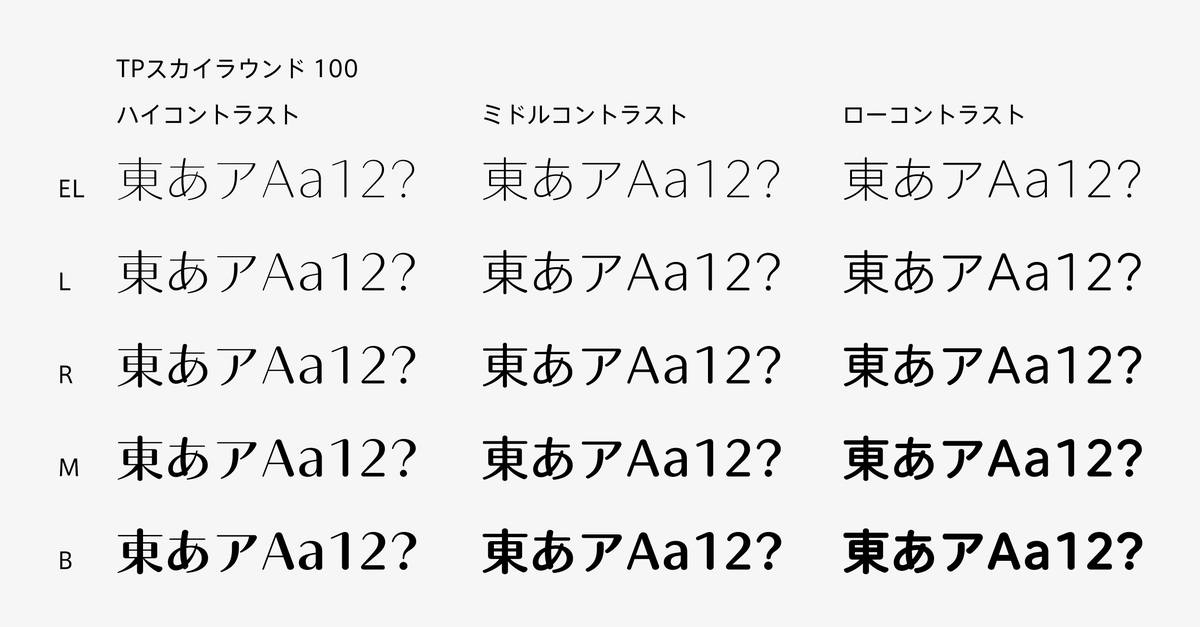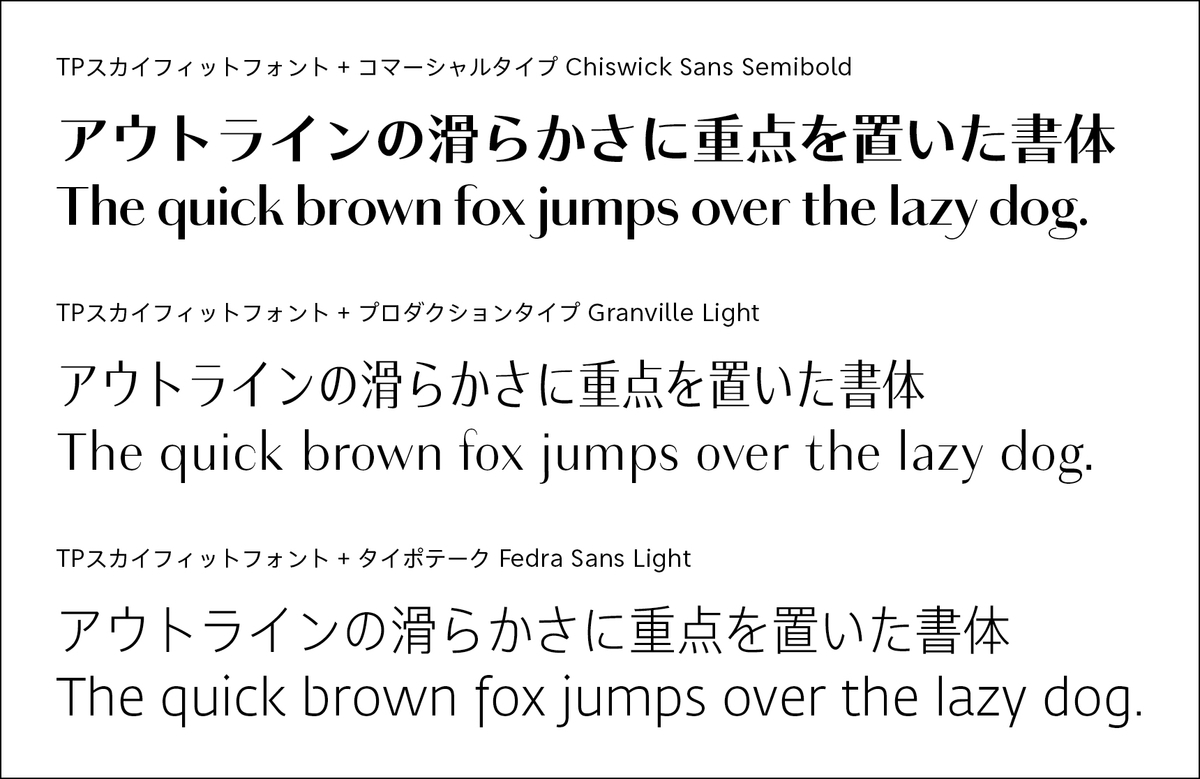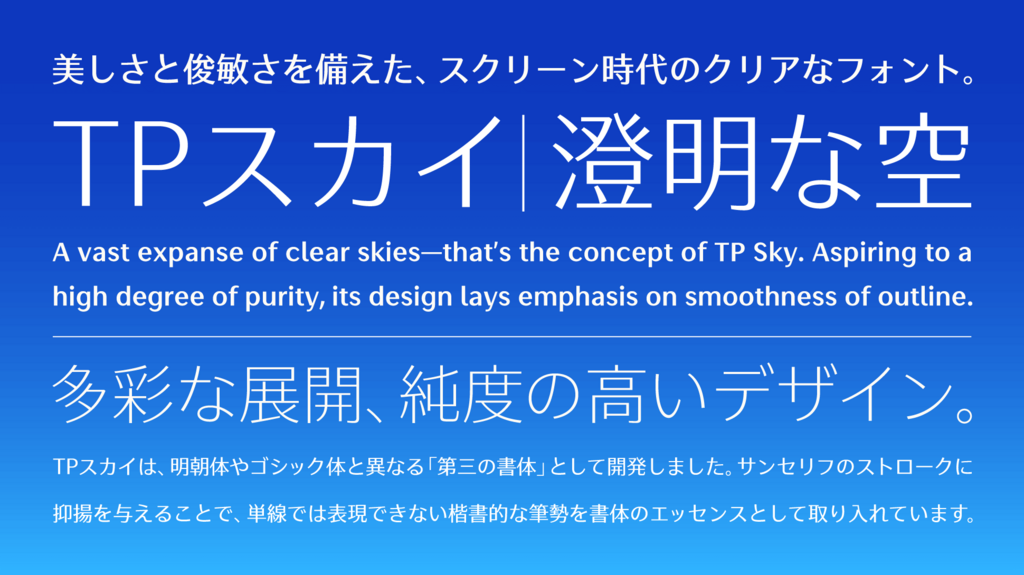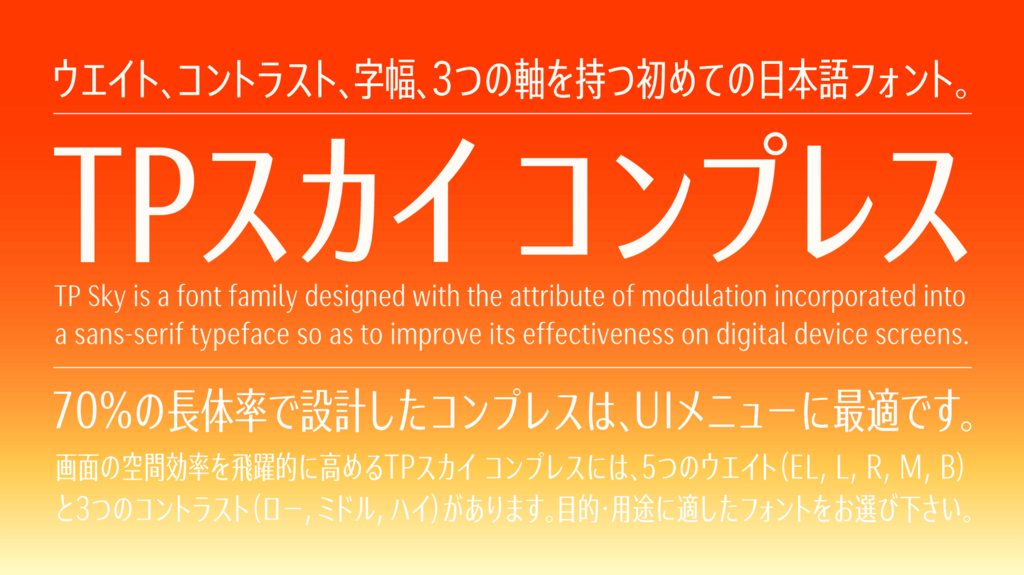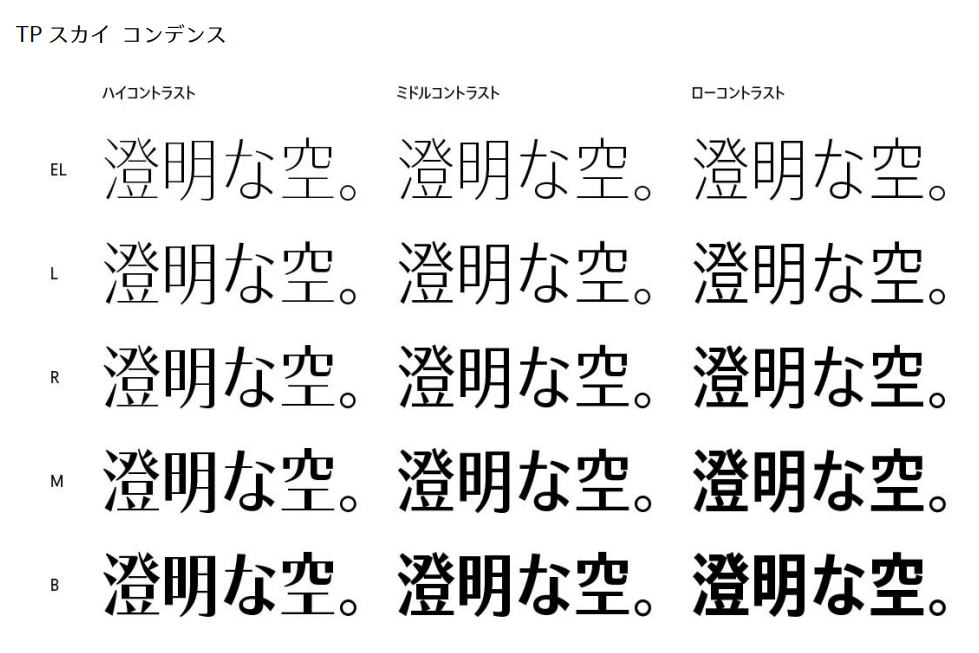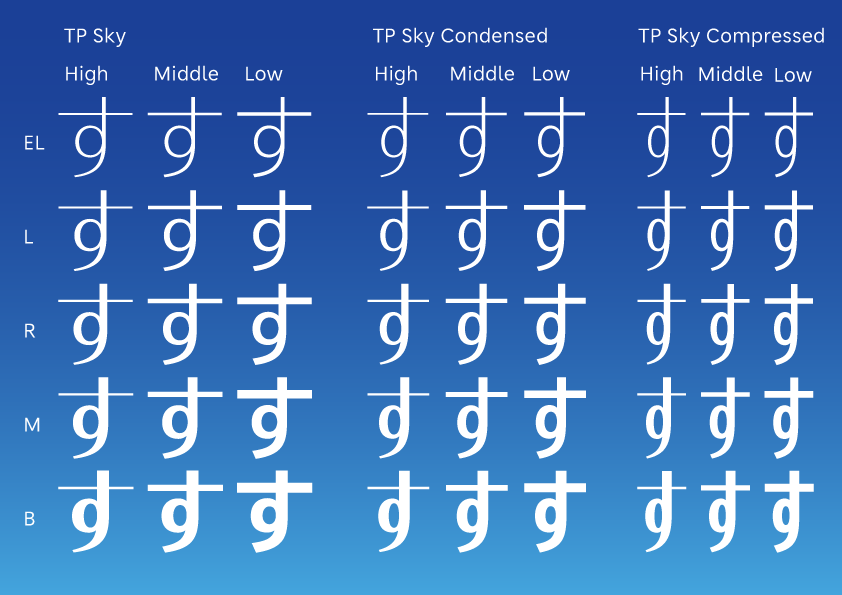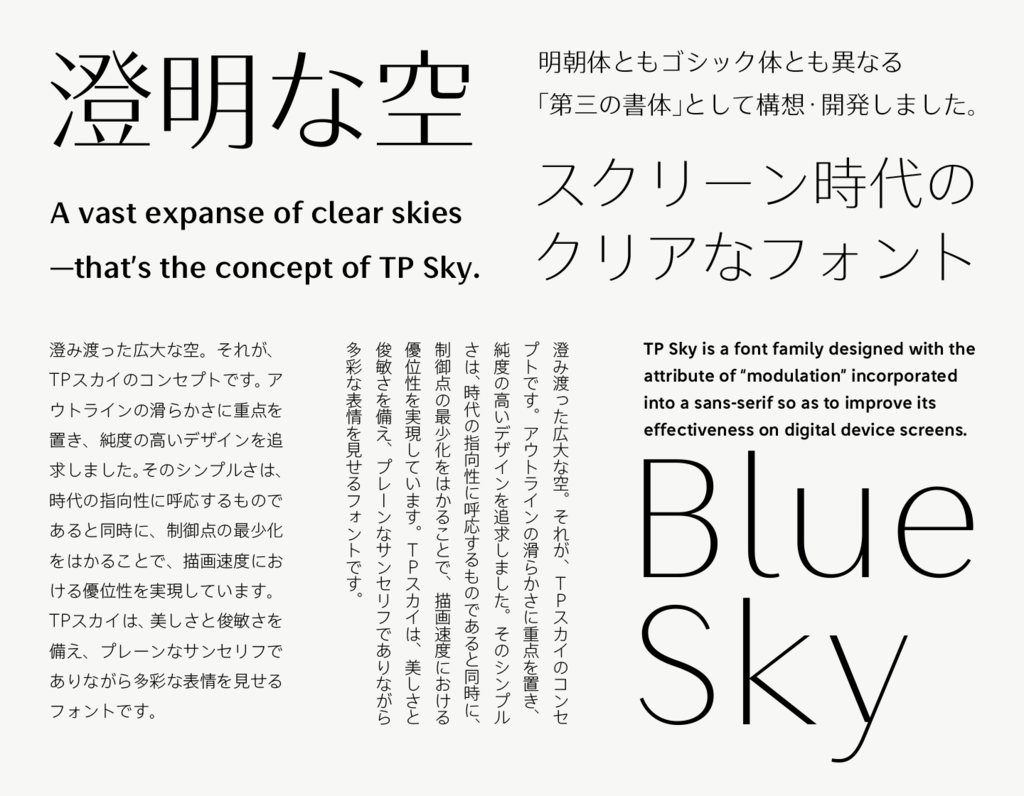
タイププロジェクトによる抑揚サンセリフ体TPスカイシリーズにラウンドフォント「TPスカイ ラウンド 50」「TPスカイ ラウンド 100」が発表
タイププロジェクトは、抑揚サンセリフ体であるTPスカイファミリーの新フォントとして、「TPスカイ ラウンド 50」および「TPスカイ ラウンド 100」を2019年5月16日に発表した。「TPスカイ ラウンドシリーズ」は、タイププロジェクトが提供するフォントを年間定額で利用できるサービス「TPコネクト」での提供となる。
「TPスカイ」は、スクリーン表示に適した本格的なフォントで、ウエイト・コントラスト・字幅の3つの軸を持つ初めての日本語フォントで、そのシリーズに、角アールの度合いを選べるラウンドが加わった。
「TPスカイ ラウンド50」と「TPスカイ ラウンド100」は、それぞれ3つのコントラスト(ハイ/ミドル/ロー) と5つのウエイト(EL/L/R/M/B) で構成され、合わせて30フォントのラウンドファミリーとなる。
タイププロジェクトの代表取締役である鈴木功氏は、「視認性が高いTPスカイの書体設計をベースに、ストロークの先端を丸めることで親しみやすさと使いやすさが格段に向上したと自負しています。横組み用途で開発したAXIS Fontに対して、TPスカイシリーズは、縦組みでの安定度も十分に考慮しました。TPスカイのラウンドシリーズは、抑揚サンセリフのカテゴリーにおける新たな定番を目指し、幅広い分野、さまざまな場面での使用に耐えうるファミリーですので、目的や用途に応じて最適なフォントをお選びいただけます」と述べている。
シャープさが持ち味のTPスカイをわずかにマイルドにした「TPスカイラウンド50」は、異なるウエイトでも同じアールに見えるよう、ウエイトによって角アールの半径を変え、視覚的なバランス調整と印象の統一をはかった。
また、丸ゴシックでありながらもすっきりと甘さを抑えた「TPスカイラウンド100」では、先端部を正円であらわしたAXISラウンドとは異なり、85%の扁平な円を採用している。
・3コントラスト :ハイ、ミドル、ロー
・5ウエイト : EL (エクストラライト)、L (ライト)、R(レギュラー)、M (ミディアム)、B (ボールド)
「TPスカイ」をフィットフォントサービスで2019年5月から提供開始
タイププロジェクトは2019年5月16日に、フィットフォントサービスを拡張し、ウエイトや字幅、コントラストを調整することが可能な「TPスカイフィットフォント」の提供を発表した。
また、サービス画面を刷新し、ウエイトや字幅、コントラストの調整に加えて、漢字、仮名、欧文の組替えも実現した。
タイププロジェクトでは、企業のメッセージを伝えるための手段としてフォントによるブランディングを提案しており、フィットフォント技術を用いて、AXIS FontやTP明朝、TPスカイのウエイトや字幅、コントラストを調節することで最適な組合せを提供している。また、欧文部を他社欧文と組替えるほか、オリジナルのひらがなやカタカナを開発するなど、世界有数のグローバル企業にコーポレートフォントを提供している。
タイププロジェクトの鈴木功氏は、「フィットフォントを基盤としたコーポレートフォント提供の機会が増えていることをとても嬉しく思っています。コーポレートフォントは、企業の声に相当するものだと考えています。自社の声にふさわしいフォントを用いることで、企業のアイデンティティを表現できるとともに、長期的かつ広汎に活用することでコストの削減にもつながります。今後も、国内外の欧文書体メーカーと協業することで、フィットフォントの導入が広がることを期待しています」と述べている。
フィットフォント
フィットフォントは、画面上のスライドバーでウエイトや字幅を調整することで、モニタのサイズやディスプレイの解像度、広告やカタログなど使用状況に応じて最適なフォントを選択できるサービス。独自開発技術により、ウエイトやコントラスト、字幅を変更した場合でも、字画の比率が適正で常にバランスの取れた状態を保ち、ダイナミックに変化しながらもデザインの一貫性と品質を保持することを実現している。
フィットフォントに対応と「TPスカイ」は、ウエイト・字幅・コントラストの3つの軸を持つ初めての日本語フォント。
TPスカイフィットフォントでは、26段階のコントラストと34段階のウエイト、 16段階の字幅で、14,144のバリエーションを用意しています。UIメニューからデジタルサイネージまでの幅広い用途や、画面のサイズや使用目的に応じて最適フォントを選択できる。さらに、今回リニューアルしたフィットフォントサービスのプルダウンメニューでは、異なるフォントの漢字・仮名・欧文を組替えて確認できるようになった。
欧文フォントでは、Commercial Type(コマーシャルタイプ、米国 ニューヨーク)の欧文書体を追加するとともに、新たにProduction Type(プロダクションタイプ、フランス パリ)とTypotheque(タイポテーク、オランダ ハーグ)の書体をリストに加わった。
〇フィットフォント導入例
・フランスの伝統的な自動車メーカーであるAlpine (アルピーヌ)には、プロダクションタイプが開発したAlpine Ascensionに合わせてAXIS Fontのウエイトを調整した「Alpine AXIS」を提供。
・株式会社デンソーへコーポレトフォントフォントとして提供した「DENSO TP 2017」と「DENSO Sans TP 2017」では、Kontrapunkt(コントラプンクト、デンマーク コペンハーゲン)が開発した欧文フォントに合わせてAXIS Font のウエイトを調整し、欧文書体の組替えを行っている。
・さくらインターネット株式会社に提供した、TP スカイのカスタマイズ版の「Haru TP」では、日本デザインセンターが制作した主要な欧文と数字をTPスカイと組合せるとともに、仮名7文字のデザインをさくらインターネットのロゴイメージに合わせて変更して提供している。
タイププロジェクトによる抑揚サンセリフ体「TPスカイファミリー」
TPスカイは、タイププロジェクトが開発・販売を手掛けるスクリーン表示に最適なサンセリフ体。
2018年4月にTPスカイの新書体として、長体ファミリーの「TPスカイ コンデンス」「TPスカイ コンプレス」が加わった。
スクリーン表示に適したTPスカイに長体ファミリー「TPスカイ コンデンス」「TPスカイ コンプレス」が2018年4月に新発売!
タイププロジェクト株式会社は、2018年4月17日にスクリーン表示に最適なサンセリフフォント「TPスカイ」の長体シリーズとして「TPスカイ コンデンス」および「TPスカイ コンプレス」を発表し、同日、発売を開始した。
TPスカイの長体シリーズ「TPスカイ コンデンス」「TPスカイ コンプレス」
「TPスカイ コンデンス」と「TPスカイ コンプレス」は、ウエイト・コントラスト・字幅の3つの軸を持つ初めての和文フォント。表示適正の高いTPスカイに長体シリーズを加えることで、美しさとともに画面の空間効率も高め、未来のスクリーンに新たな文字表現をもたらした。
アウトラインの滑らかさに重点を置き、簡潔な文字描画によってフォントデータの軽量化を実現したTPスカイファミリーに長体シリーズが加わったことで、5ウエイト、3コントラスト、3 つの字幅の全45フォントとなった。
長体でデザインした真のコンデンス体であるTPスカイ コンデンスは、漢字と仮名ともに 85%の長体率で設計、コンプレスは 70%の長体率で設計された。
コンデンス、コンプレスともに、フォルムとカウンターのバランスを丁寧に整え、画線の太さと文字の黒みを徹底的に揃えることで、サンセリフ体のフォントに期待されるフラットな質感を高いレベルで実現した。
タイププロジェクトがスクリーン表示に適したサンセリフ体フォント「TPスカイ」を発表!
タイププロジェクト株式会社は、2017年4月17日にスクリーン表示に最適なサンセリフフォントとして「TPスカイ」を発表した。